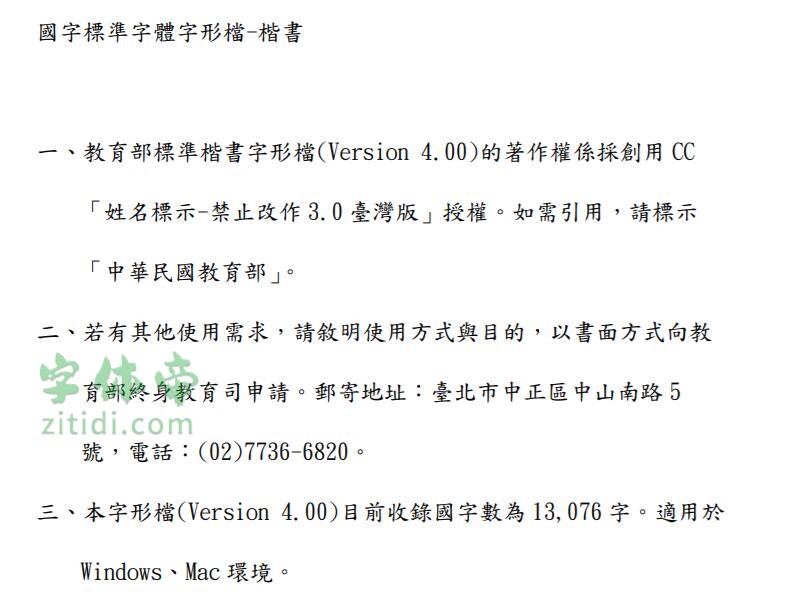
台湾教育部标准楷书是针对台湾地区而开发一款实用的标准楷书字体,该字体线条粗细适中,整体效果出色,台湾教育部推出,字形扁方左右分展,化圆为方化弧为直,端正秀美。该字体包含4391个简体中文、字母、 符号和数字,具有古典、中国风、大气 的风格,可以满足您设计上的各种需求。
“台湾教育部标准楷书”是一款书写很新颖的字体,字体大方,适合各种设计作品使用!欢迎下载!